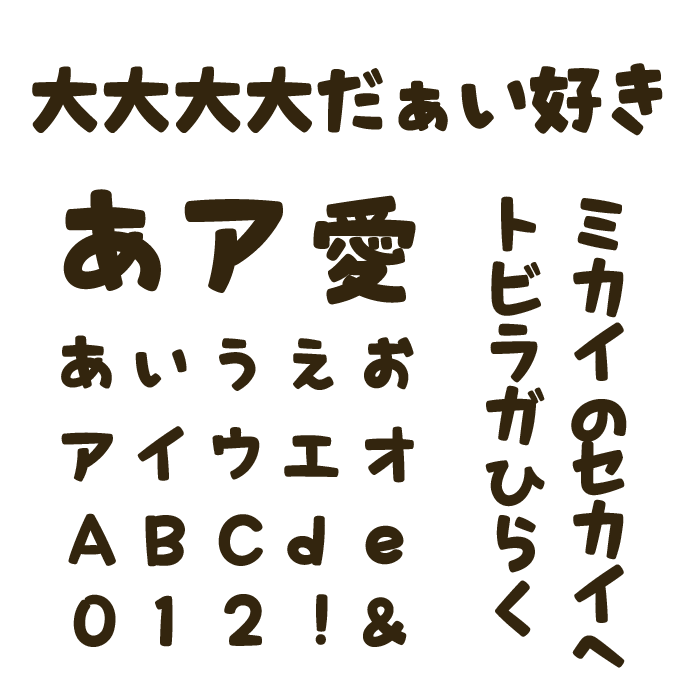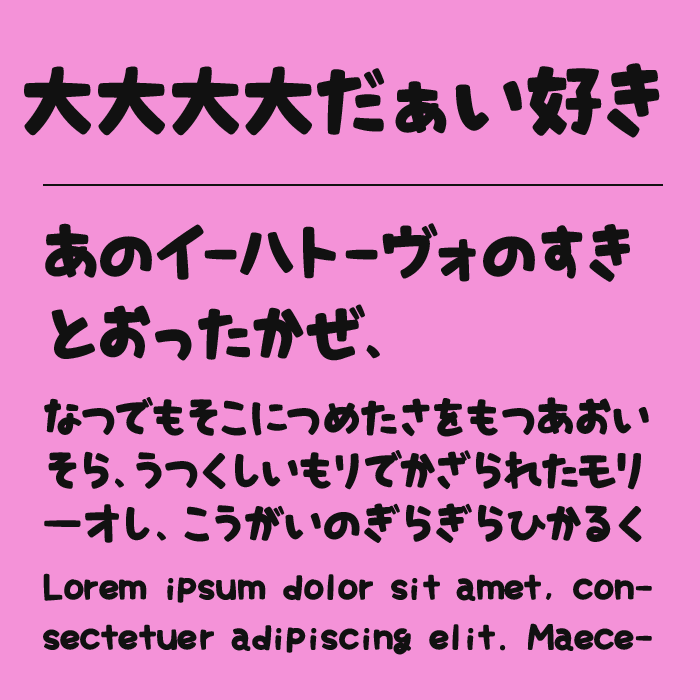
大大大大だぁい好きは、マーカーや太めのペンで勢いよく書いたような、丸みのある手書きフォントです。
文字の大きさや傾きがほんの少しずつ揃っておらず、その不揃いさがかえって自然で、手で書いた文字ならではの親しみやすさがあります。
かわいい雰囲気はありながら、線がしっかり太いため甘くなりすぎないのもポイントです。SNSの画像や動画のテロップ、ポップ、ステッカー風のデザインなど、元気な言葉を大きく見せたい場面によく合います。
「好き!」「最高!」のような感情のこもった言葉とも相性がよく、文章よりも短いフレーズで使いたくなるフォントです。